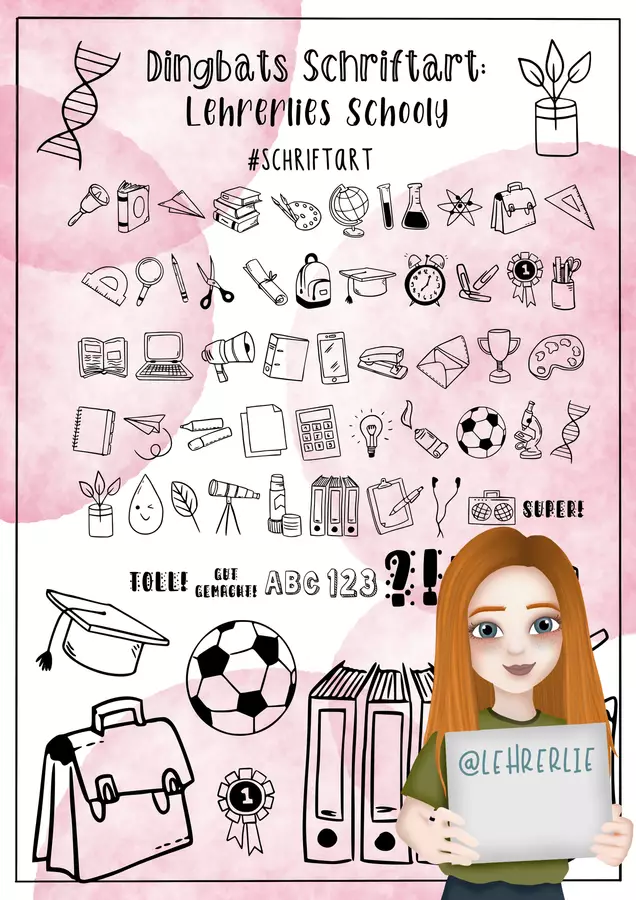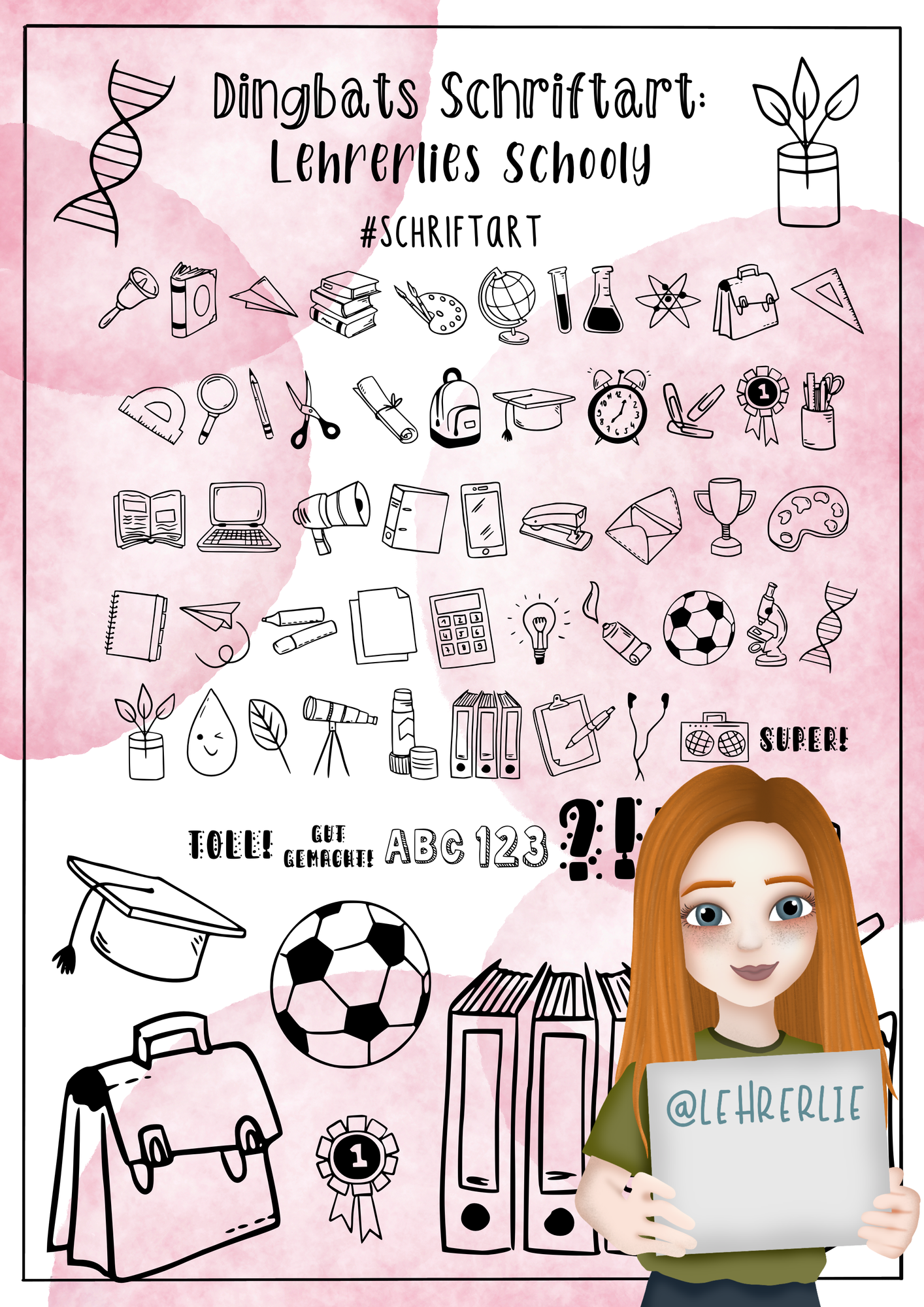
Hier bekommt ihr eine Symbolschriftart mit vielen tollen Zeichen rund um das Thema Schule! Damit könnt ihr super einfach jedes Arbeitsblatt direkt in Word unc co. aufpimpen. Die Schriftart ist genau wie eine normale Schriftart einfach zu installieren und kann dann verwendet werden!